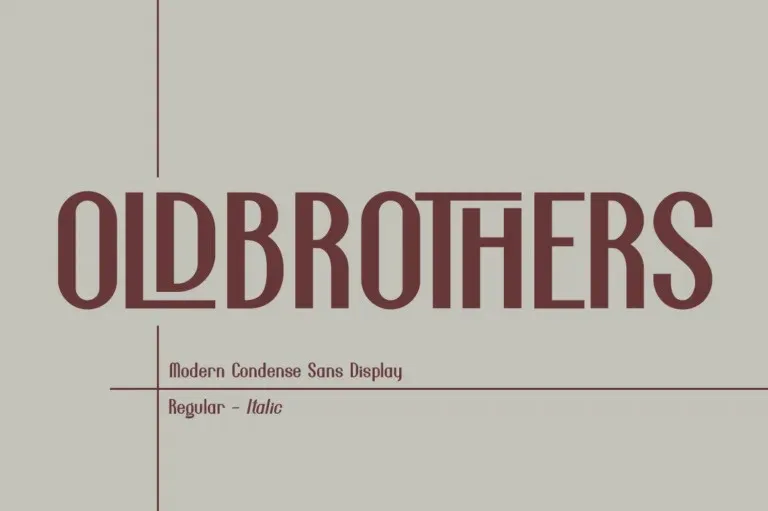
Esta fonte sans-serif foi desenvolvida pelo Haksen Studio e apresenta uma elegância única que se destaca graças aos ligantes utilizados para unir as letras num processo suave e fluido. Com sua ampla variedade de ligantes maiúsculas, ela oferece um leque vasto de opções para design, tornando-a perfeita não apenas para headlines e logotipos, mas também para aplicações como posteres, embalagens, camisetas, cartões-postais e muito mais. Ela traz uma dose única à sua próxima criação visual, oferecendo uma forma moderna de expressar seu estilo com cada projeto que desenvolver.